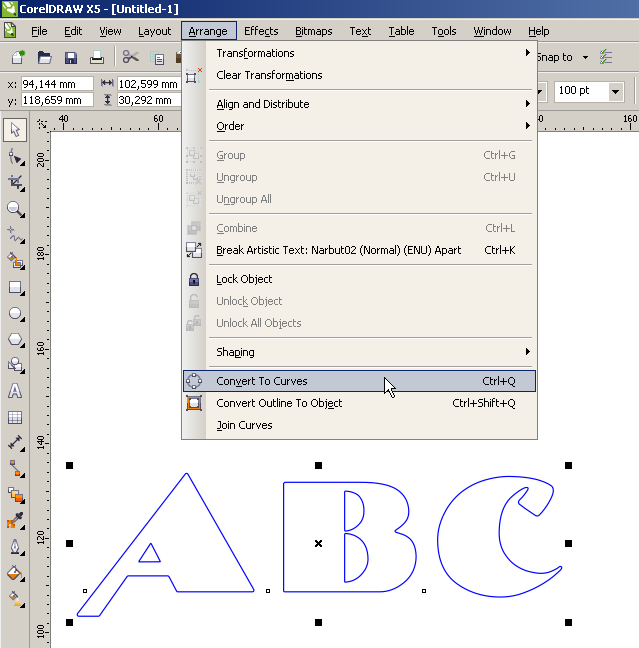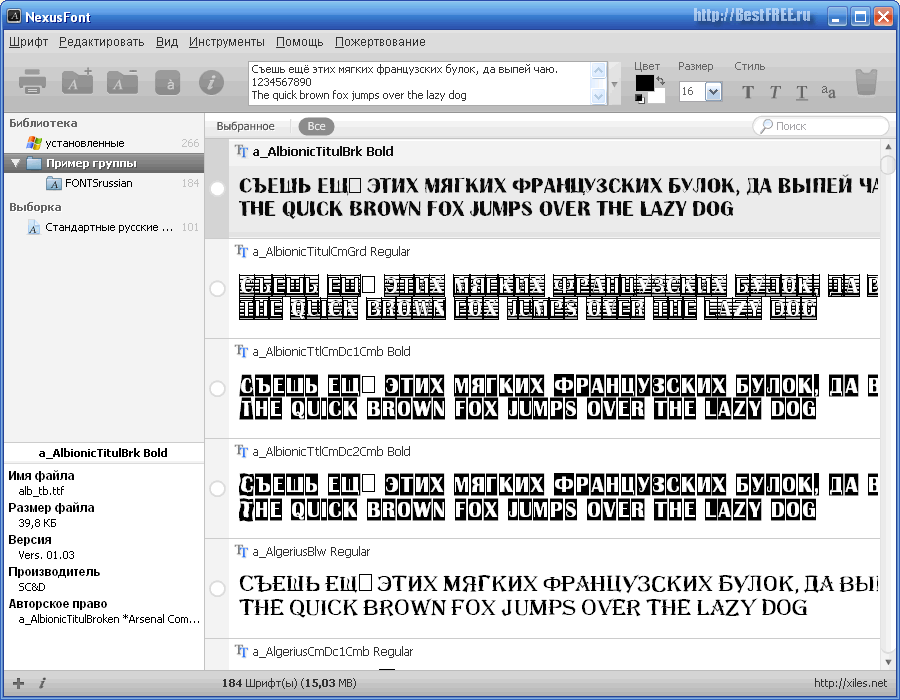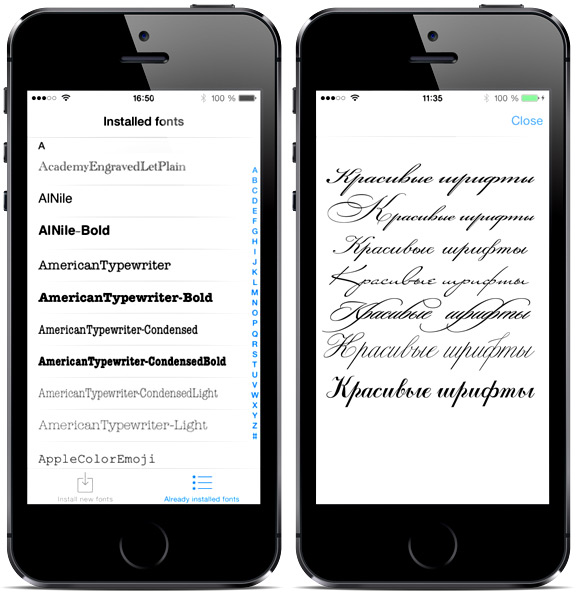
Выбор шрифта для тату онлайн. Программа для создания эскизов татуировок
Татуировки в виде надписей приобретают все большую популярность. Большую роль играет правильный выбор шрифта, ведь их существует очень много. Нужно учитывать стиль написания, месторасположение рисунков, размер слов. Заглавная буква должна быть выделена наклоном, цветом или стилем нанесения.
Красивый шрифт на ноге
Различные вариации шрифтов позволят сделать татуировку в виде надписи красивой и оригинальной
Особенности татуировки шрифты
Татуировки в виде надписей смотрятся очень оригинально и красиво. Их очень любят наносить на свое дело голливудские звезды. В некоторых случаях надпись способна передать смысл татуировки даже лучше чем рисунок. Для этого очень важно подобрать правильный шрифт. Для женских надписей подойдут шрифты с глубокими изгибами, тонкими линиями и дополнительным декором. Для мужских надписей нужно обратить внимание на печатные буквы, применение жирного начертания, заостренные окончания.
Татуировки шрифты, значение которых больше зависит от смысла самой надписи, одинаково распространены, как среди женщин, так и среди мужчин.
Выбираем язык и дизайн заглавной буквы
Как правило, шрифт зависит от языка. Однако наибольшей популярностью пользуется английский язык , поскольку он считается мировым. Для татуировки надписи, как правило, выбирают шрифты с вензелями и каллиграфические шрифты. Перед нанесением на свое тело надписи нужно определиться: будет ли это слово или целая фраза. Если вы хотите сделать надпись, которая начинается с заглавной буквы, то нужно обсудить с дизайнером ее особенности, поскольку не каждая заглавная буква будет хорошо смотреться. Возможно, дизайнер предложит вам выделить ее отдельным цветом или украсить дополнительными элементами. Татуировки шрифты, фото которых вы найдете не только на просторах интернета, а и в тату-салонах, позволят вам подчеркнуть свою индивидуальность.
Шрифт для татуировки в виде надписи может быть самым разным.
Если вы сомневаетесь в выбранном стиле, лучше посоветуйтесь с дизайнером.
Четкая надпись сбоку тела у девушки
Правильно подобранный шрифт – это основа красивой татуировки в виде надписи
Любая надпись на теле должна быть читаемой, иначе она не сможет передать тот смысл, который вы хотели в нее вложить. Откажитесь от применения слишком мелких шрифтов, а также тонких линий, близко расположенных друг к другу. Любое тату с течением времени слегка расплывается, поэтому ваша надпись может превратиться в одно сплошное пятно.
Виды шрифтов для нанесения татуировок в виде надписей
Татуировки шрифты, эскизы которых есть в каталогах салонов для нанесения татуировок, бывают нескольких видов. В современных тату-салонах отдают предпочтение следующим видам шрифтов:
- каллиграфическим;
- готическим;
- граффити;
- западным
Надпись на запястье, красивый шрифт
Есть и другие виды, но именно эти пользуются наибольшей популярностью.
Стоит рассмотреть их особенности более подробно.
Каллиграфические шрифты
Этот шрифт выбирают по многим причинам. Он наиболее разборчив и понятен, вы без труда сможете выбрать буквы и знаки, наиболее подходящие по стилю для вашей татуировки. Каллиграфический шрифт может быть классическим, который сделает вашу татуировку похожей на старинную надпись, а также простым, в котором используются обычные буквы, написанные от руки .
Совет. Для того чтобы ваша татуировка в виде надписи смотрелась красиво и оригинально, подбирайте шрифты с помощью специальных программ и сайтов. Современные технологии позволяют сделать это даже не очень уверенным пользователям.
Готический шрифт
Этот шрифт начали использовать музыкальные коллективы для написания своих логотипов. Готический шрифт может быть как сложным, так и простым. От этого будет зависеть легкость чтения готовой надписи. Можно использовать отдельные инициалы или целые надписи.
Я хотела нанести на свое тело имя своего ребенка.
Хотелось подобрать красивые буквы. Я решила не пользоваться никакими программами, а сразу пошла в салон. Здесь мне помогли выбрать шрифт, который мне идеально подошел!
Лера, Ярославль
Стиль Граффити
Этот стиль представляет собой смешение иллюстрации и топографического шрифта. Он пришел буквально с улиц. Идеи для вдохновения вы можете черпать даже с тех надписей, который вы сможете увидеть на заборах и во дворах. Однако нужно помнить о том, что не каждый дизайнер сможете нарисовать татуировку в таком стиле.
Граффити на плече парня
Даже очень маленькая татуировка может придать вашему образу особую пикантность
Совсем недавно у меня возникла идея нанести на свое тело татуировку со словом «Вечность». Я просто открыл «Фотошоп» и подобрал нужный шрифт. Дизайнер одобрил результат моей работы.
Западный шрифт
Надпись, выполненная при помощи такого шрифта, перенесет вас во времена Дикого Старого Запада.
Надпись в виде шрифта из одной линии
Азиатские, арабские, русские шрифты
Некоторые любители тату выбирают надписи, которые напоминают о той или иной цивилизации или стране. Вовсе не обязательно использовать буквы, которые используются в той или иной стране. Можно просто стилизовать надпись. Смотреться такая татуировка будет также очень красиво.